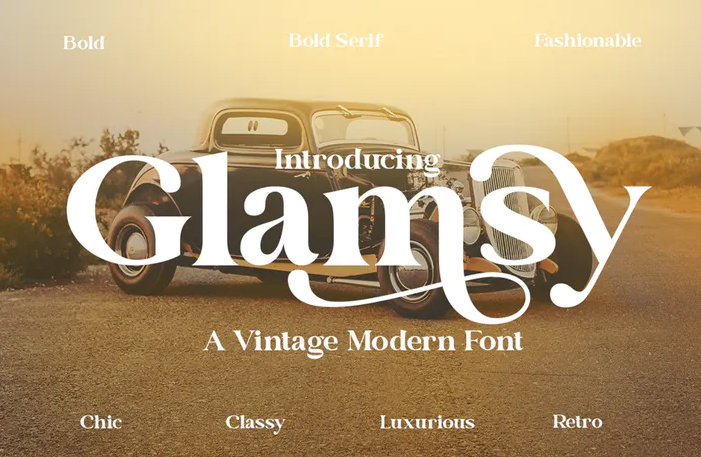
Представляем Glamsy - винтажный современный шрифт.
От товаров и печатных материалов до веб-сайтов и кампаний в социальных сетях - Glamsy готов для любого проекта.
Попробуйте и убедитесь, какое влияние может оказать шикарный шрифт.